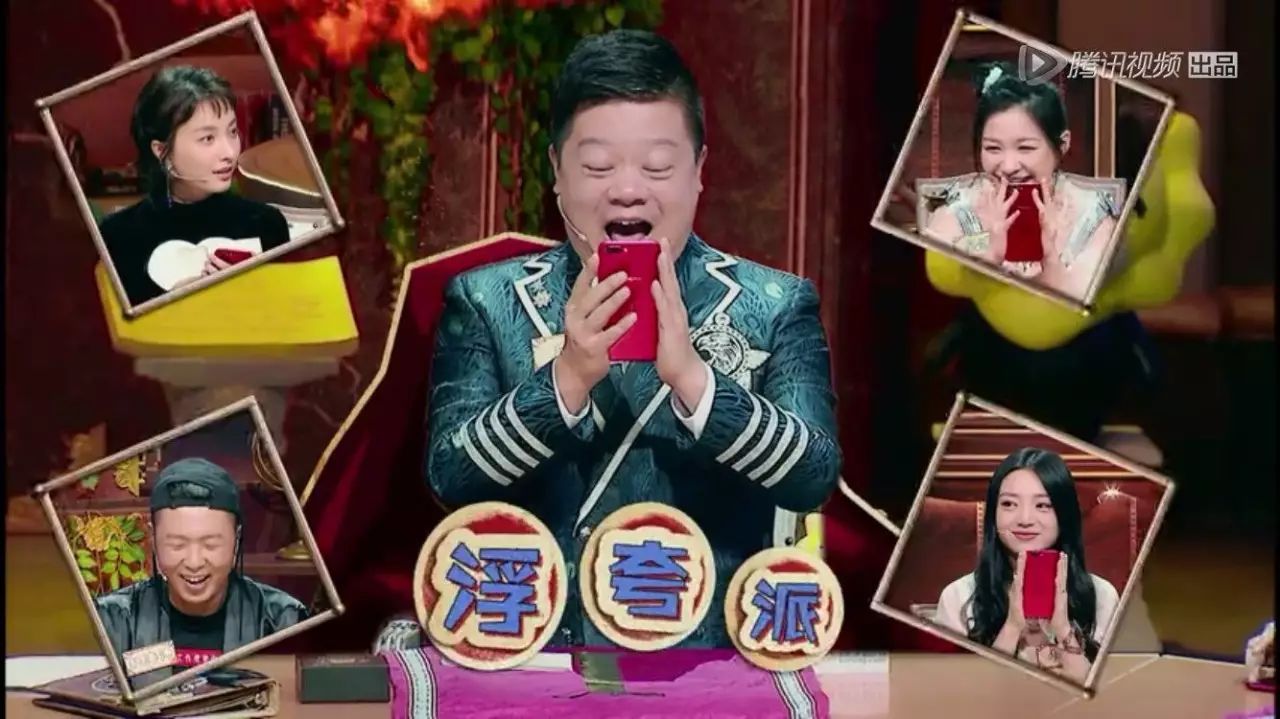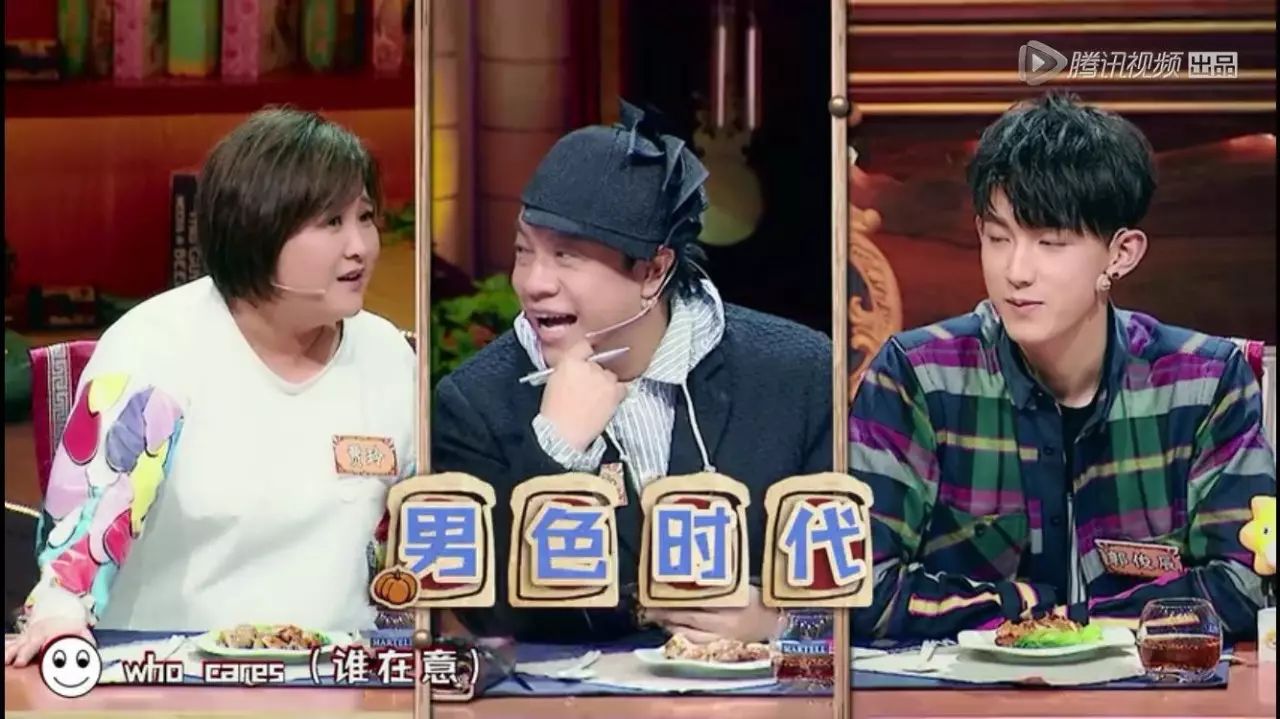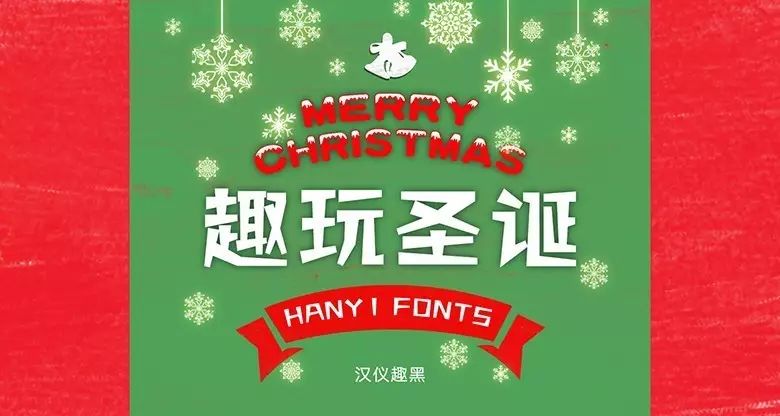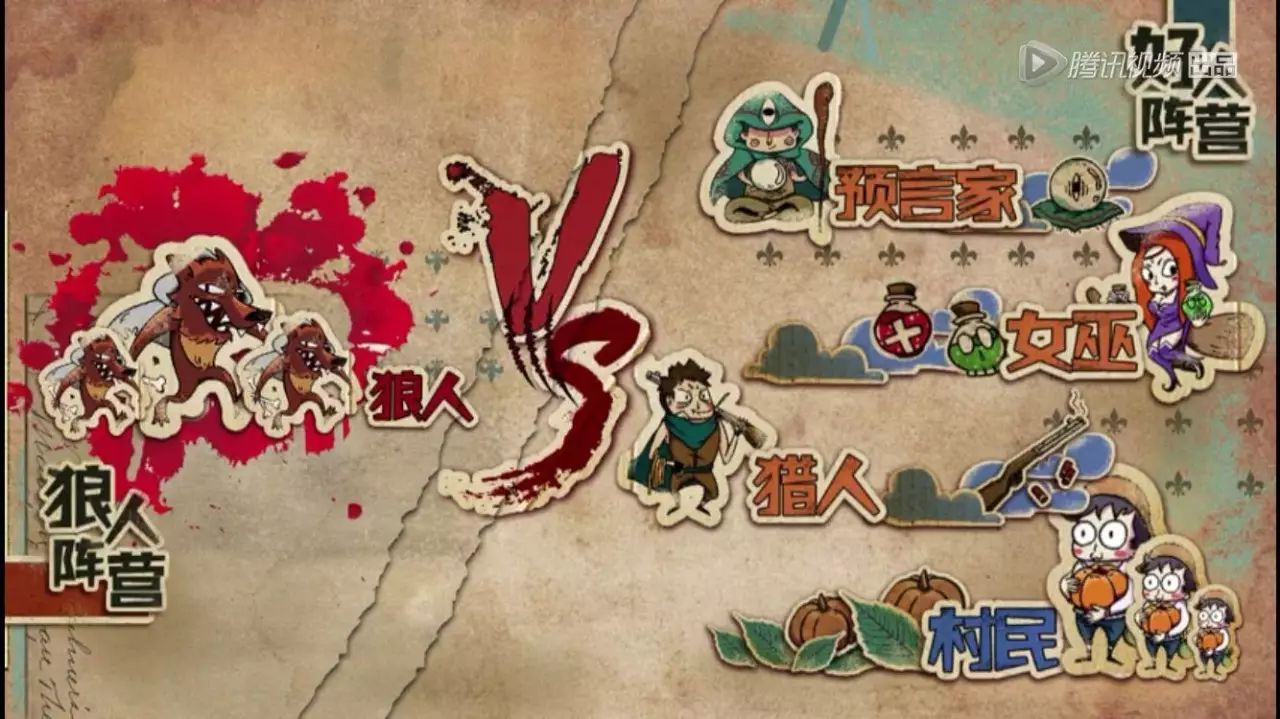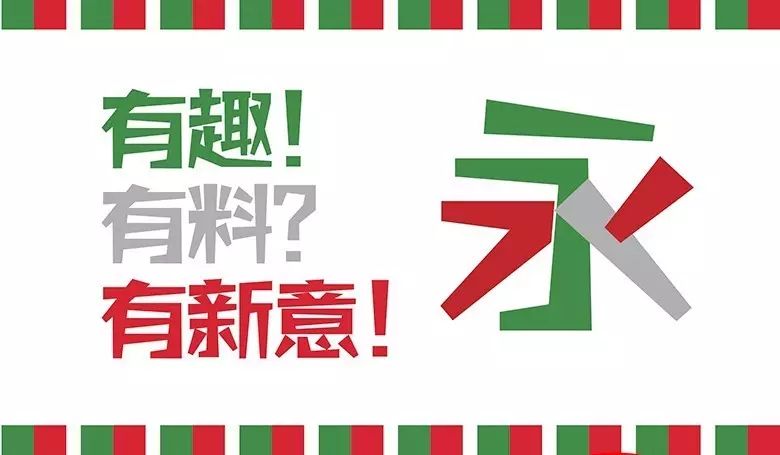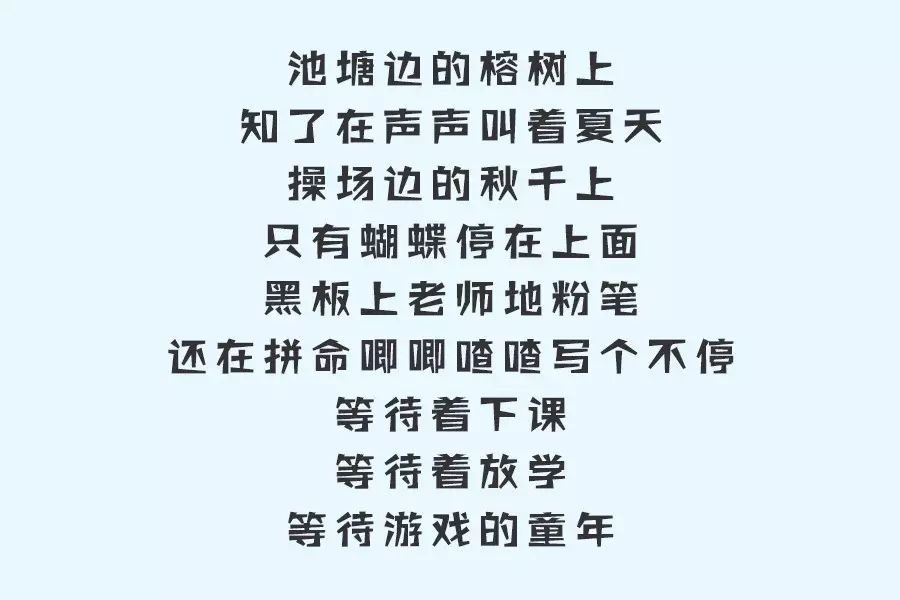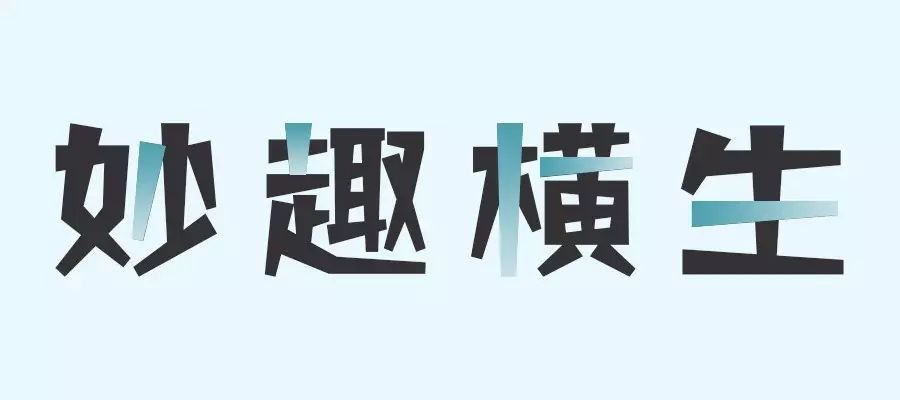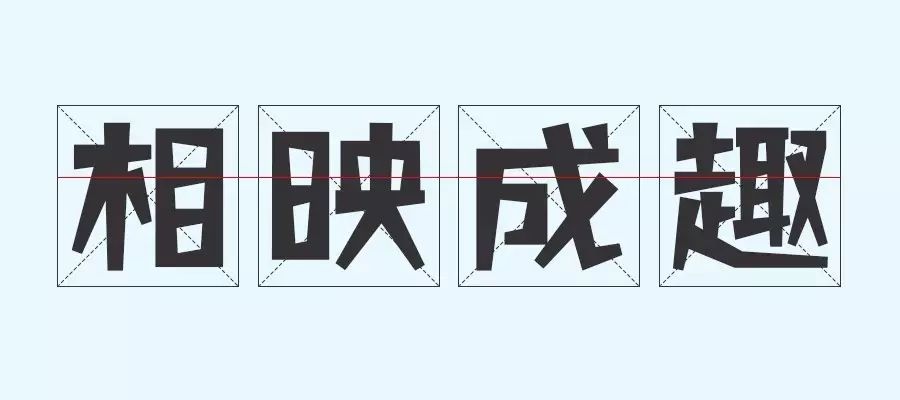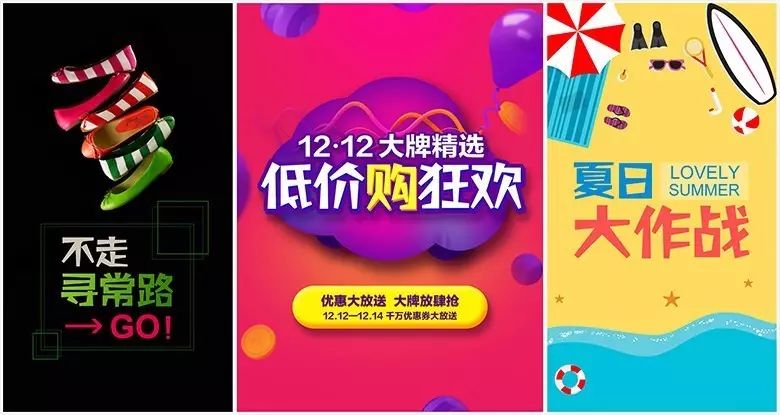
节目中那些有趣的字体,适合节目字幕的字体分享
要么就会写 要么就会用
字随便你选 由我来填满
这个字体的诱惑。。
听说大家都在看某局诱惑2.0版
节目不单单为观众带来了很多乐趣
同时里面那些有趣的字体也是让人眼前一亮。
字体作为节目效果的点睛之笔
很多网友纷纷留言表示想入手这些好玩的字体
小编今天就为大家做个分享
说一说节目中那些有趣的字体
某局诱惑2.0字幕中
那如积木拼接起来的俏皮字体
叫作汉仪趣黑体
汉仪趣黑主打轻松俏皮风
和某局的精神主题不谋而合
这也许就是选趣黑做字幕的理由之一
但毕竟是用在屏显上
良好的辨识度才是作字幕最重要的本质
从上面可以看出
趣黑在保证整体风格的前提下
字体辨识度表现也是很优秀的
趣黑看似是随意拼接组成
实则每笔都有着自己的“秩序”
单独部件
保持粗细变化间的重量平衡
在不影响重心的情况下
保持起笔粗收笔细的变化节奏
正是因为这些内在的“秩序”
才使得趣黑变化虽然丰富
但始终保持方正的外形和
稳定的重心
夸了这么多实在是夸不动了
直接上案例👇
大家自己体会趣黑的
神奇之处吧!